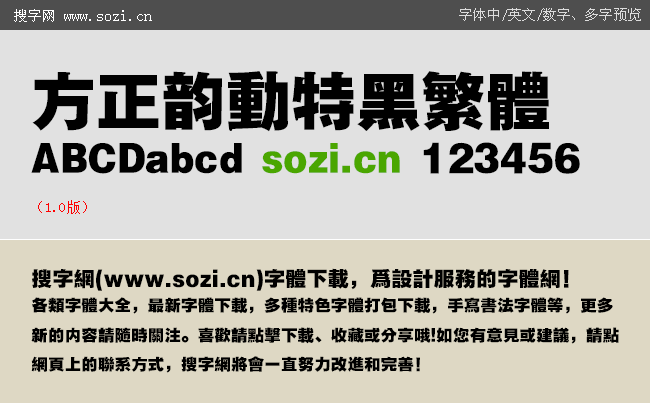
方正韻動(dòng)特黑繁體(FZYDTHFW)
搜字網(wǎng)提供一款方正韻動(dòng)特黑繁體中文字體下載,韻動(dòng)黑去掉了原黑體筆畫上的喇叭口裝飾,使字體風(fēng)格更加簡(jiǎn)約時(shí)尚。在豎、撇、提的起筆處增加了裝飾頭,使字體更具個(gè)性。在撇、捺、點(diǎn)的設(shè)計(jì)上力求角度自然合理,不僅舒展有度,而且富有彈性和力度;豎鉤的長(zhǎng)短適度,轉(zhuǎn)折靈活。對(duì)字面適當(dāng)加以擴(kuò)大,使字體更加莊重平穩(wěn),增強(qiáng)了版面的視覺(jué)沖擊力。適合書籍設(shè)計(jì)、展板設(shè)計(jì)、海報(bào)設(shè)計(jì)等廣告設(shè)計(jì)場(chǎng)合使用。